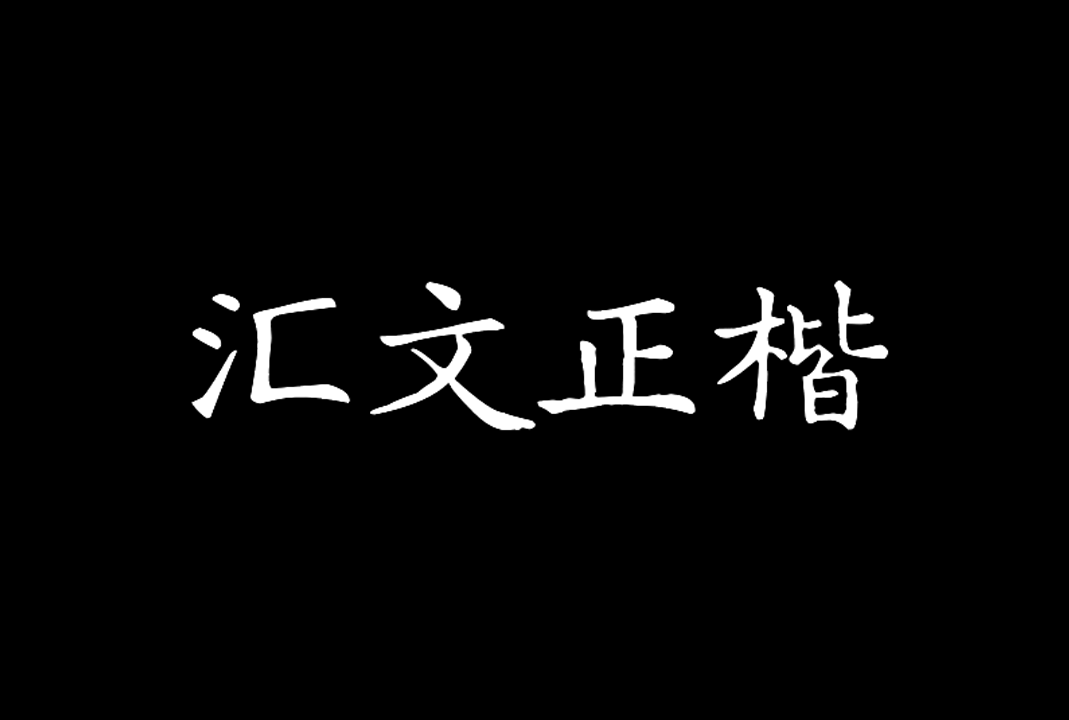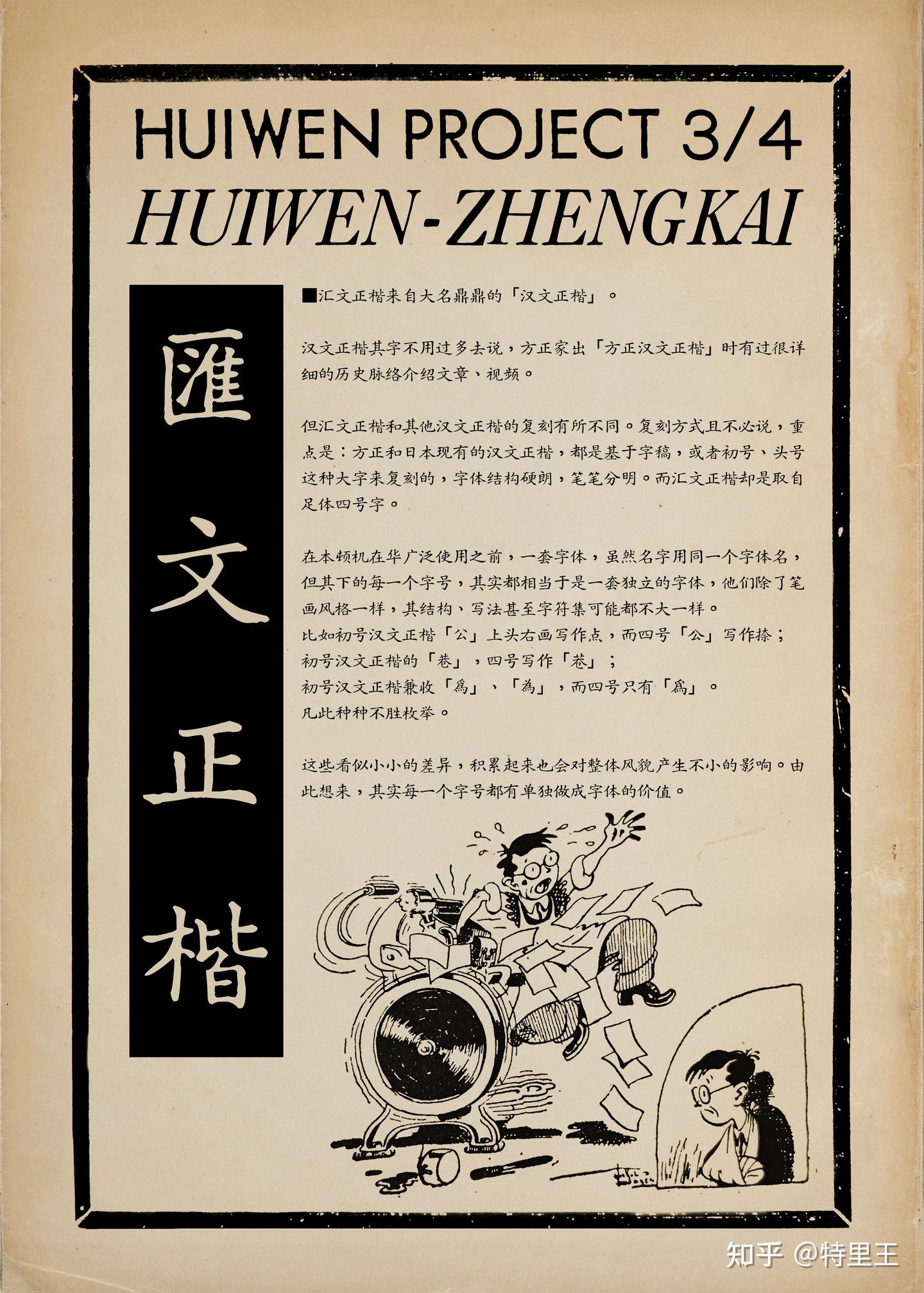
汇文正楷_免费中文复古印刷字体下载
汇文正楷是一款由网友特里王发布的一款免费商用的中文复古印刷字体,该字体为汇文系列(仿楷黑明)之正楷。该字体的字形来自大名鼎鼎的「汉文正楷」。
但汇文正楷和其他汉文正楷的复刻有所不同。复刻方式且不必说,重点是:方正和日本现有的汉文正楷,都是基于字稿,或者初号、头号这种大字来复刻的,字体结构硬朗,笔笔分明。而汇文正楷却是取自足体四号字。
# 补充知识:
在本顿机在华广泛使用之前,一套字体,虽然名字用同一个字体名,但其下的每一个字号,其实都相当于是一套独立的字体,他们除了笔画风格一样,其结构、写法甚至字符集可能都不大一样。
比如初号汉文正楷「公」上头右画写作点,而四号「公」写作捺;初号汉文正楷的「巷」,四号写作「巷」;初号汉文正楷兼收「爲」、「為」,而四号只有「爲」。
这些看似小小的差异,积累起来也会对整体风貌产生不小的影响。由此想来,其实每一个字号都有单独做成字体的价值。